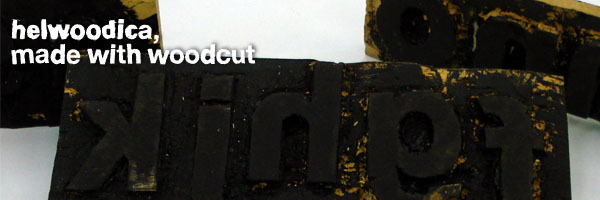
FD Helwoodica autorstwa Felipe Dario to darmowy, poszarpany font tytułowy o tępych, masywnych kształtach liter. Jego nierówne krawędzie i wyszczerbione powierzchnie przypominają tusz wciśnięty w papier. Kształty sprawiają wrażenie celowo zniszczonych.
Ta surowa konstrukcja pasuje zarówno do plakatów muzycznych, jak i surowych opakowań żywności, nadając każdemu z nich wygląd ręcznie drukowanych szyldów. Sprawdzi się także w odzieży streetwearowej oraz oprawie graficznej imprez opartych na motywie undergroundowym lub DIY. Powtarzające się pęknięcia i poszarpane kontury pozwalają literom funkcjonować jako część zużytej tekstury druku.